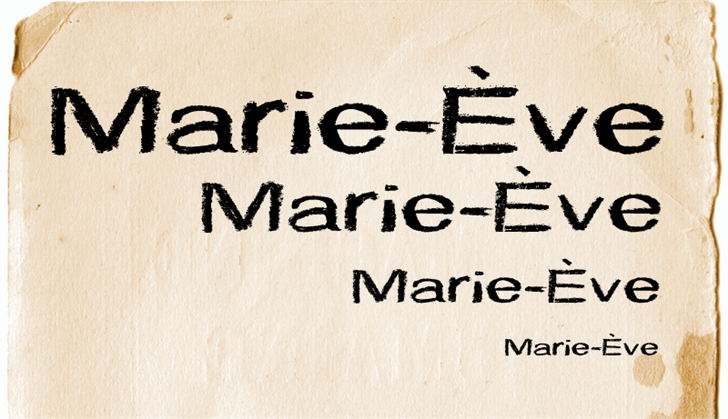
A CF Marie Eve é uma fonte tipográfica que traz consigo um charme vintage ao seu design, agradavelmente adaptado para um uso moderno. Inspirada no estilo dos typewriters de geração anterior, esta fonte oferece um toque retro e elegante. Ela foi projetada por Hamilton, resultado do amadurecimento em estilos antigos combinados com elementos contemporâneos. Aventura-se na classificação ‘Typewriter Fonts’ para encontrar uma fonte que atende aos seus requisitos de design sem comprometer a funcionalidade e sofisticação. Essa CF Marie Eve não apenas se ajusta perfeitamente ao seu site ou aplicativo, mas também transmite um sentimento nostálgico e autêntico. Com o uso dela, você oferece uma experiência única para os seus usuários. Para aqueles que querem explorar mais esse design tipográfico e ter acesso a uma ampla gama de caracteres, Hamilton permite compras de licenciamento. Por outro lado, essa fonte está disponível gratuitamente para uso pessoal (à utilização não lucrativa). Compre sua própria licença se desejar usar a CF Marie Eve em um ambiente comercial ou para aumentar ainda mais seu catálogo de recursos gráficos personalizados.